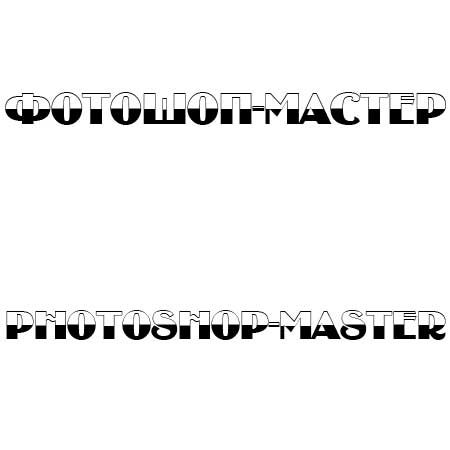
Очень нужен - для стиля под прозрачность
Некоторым, возможно, он нужен!
Не понимаю, зачем нужен такой шрифт, когда можно использовать градиент для любого шрифта....